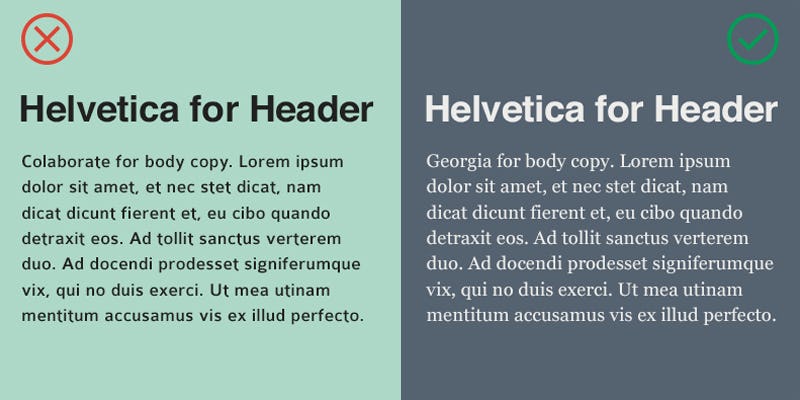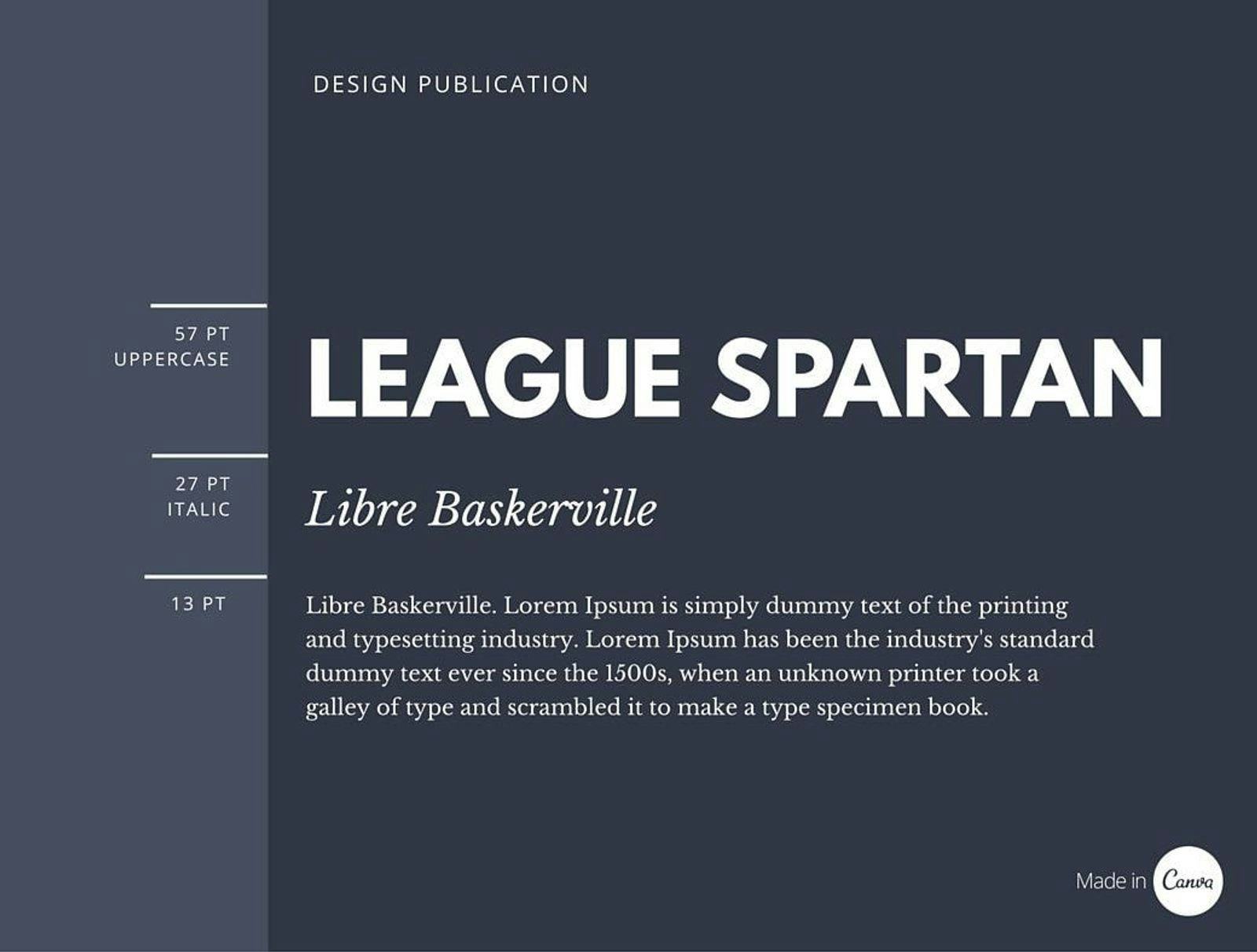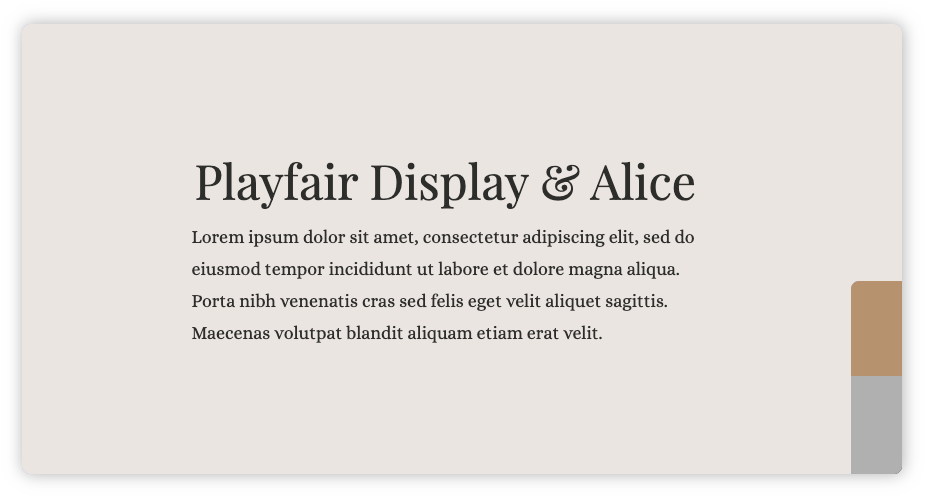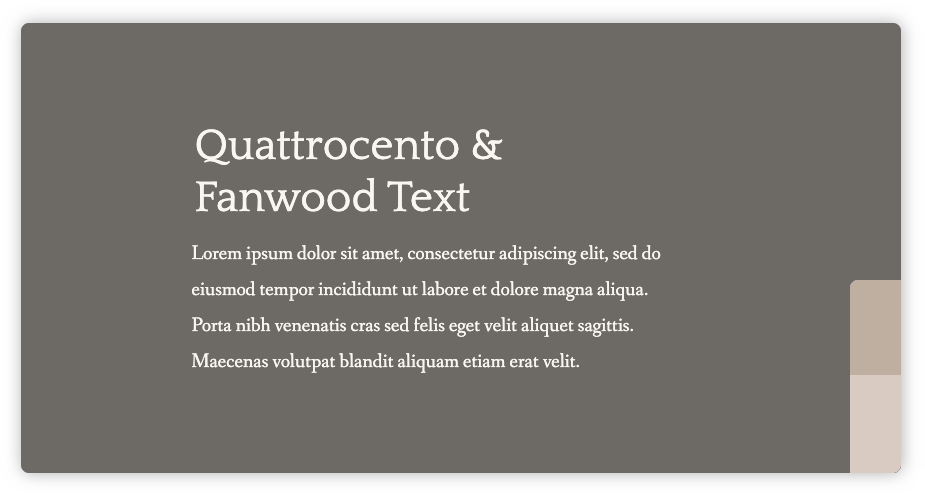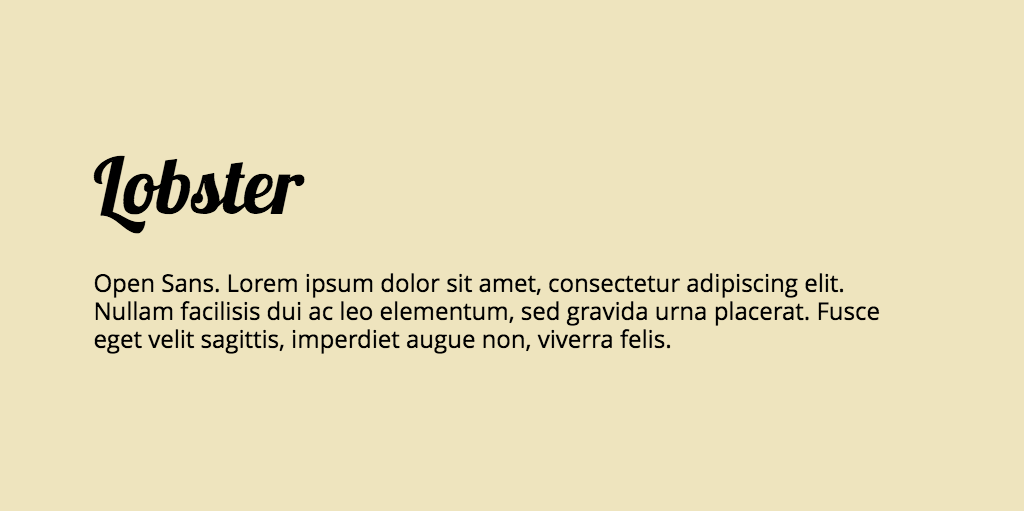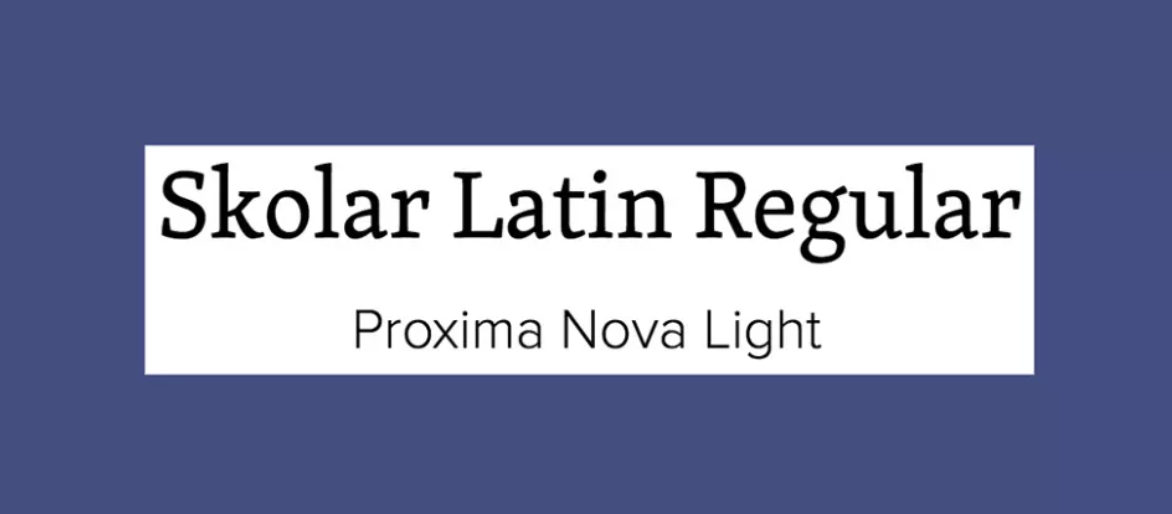
¿Te has puesto a pensar cuál es la mejor forma de combinar tipografías en un diseño? Si estás trabajando en proyectos artísticos y necesitas utilizar mucho contenido tipográfico es importante que consideres un match perfecto de fuentes que sea coherente lo que quieres comunicar.
¿Sabes cómo hacerlo? Nosotros te explicaremos en esta nota cuál es la mejor forma de combinar fuentes, qué reglas tipográficas no debes romper y cuáles son las mejores combinaciones tipográficas para hacer un match en diseño.
¿Te imaginas que tus trabajos puedan formar parte de los proyectos de diseño más populares? Aprender sobre la combinación de tipografías te puede ayudar a volver ese sueño una realidad.
1. Comprende el papel de la tipografía en el diseño
Para aprender cómo combinar tipografías, debes considerar algunas cosas, en especial, entender el papel que juegan las tipografías en el diseño gráfico. Aspectos como el contraste tipográfico y la legibilidad, entre otras cosas, hacen que un diseño bueno se diferencie de uno que no lo es.
No te preocupes si no entiendes mucho de lo que te hablamos, porque te comentaremos cada uno de los aspectos que tienen peso en el uso de las combinaciones tipográficas.
Contraste tipográfico
Si decides utilizar tipografías similares puedes crear contrastes tipográficos aplicando distintos estilos como por ejemplo: negrita, cursiva, mayúscula o minúscula.
Esta es una forma fácil de combinar las tipografías sin preocuparse de hacerlo mal, si necesitas hacer contenido de fácil lectura, utilizar fuentes similares es un excelente recurso.
Un ejemplo de contraste tipográfico es combinar una fuente negrita como Futura Medium con una letra similar; pero más delgada.
Las diferencias de estilo tipográfico hacen que el contenido en una página web o en cualquier medio digital sea más fácil de leer.
Legibilidad en la combinación de fuentes tipográficas
Una de las razones principales para combinar fuentes tipográficas serifs es la legibilidad de lectura en los libros y periódicos.
Las serifs, en la parte superior o inferior de un texto, facilitan a cualquier lector la comprensión entre caracteres de aspecto similar como la “l” mayúscula y la “l” minúscula”
Y si encuentras un sans serif con distintas formas de letras; pero legibles, no tengas miedo de experimentar y usarlas en el cuerpo del texto.
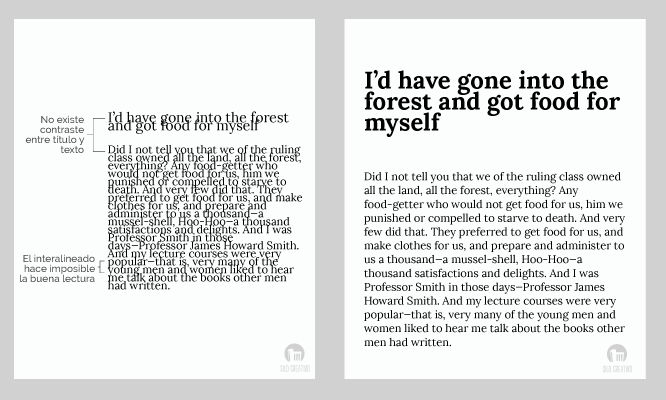
Comodidad en la combinación de letras
Muchos diseñadores web tienen el temor de utilizar una combinación de letras clásicas porque piensan que es “más de lo mismo”. Y fuentes tipográficas como Helvetica o Times New Roman muchas veces quedan en el olvido por su uso excesivo.
Sin embargo, la selección y combinación de fuentes se debería hacer pensando qué tan cómodo se siente el público al momento de leer la información de un sitio web, por ejemplo.
Por eso, no tengas vergüenza en elegir las clásicas fuentes tipográficas, sobre todo, si hacen un buen match con el diseño de un sitio web.
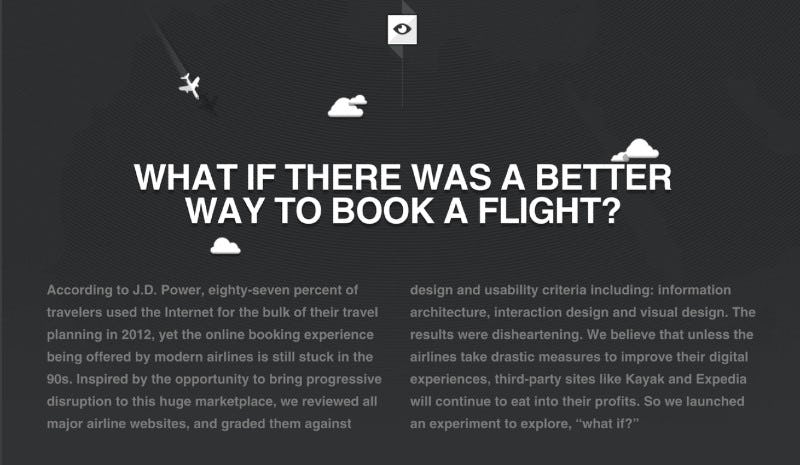
Combinación de letras para logos
Escoge tipos de fuentes con estilo que se alineen con la marca de tu cliente. La mejor forma de hacerlo es combinar letras que tengan un peso visual en el diseño de los logos.
Ten en cuenta que además de utilizar negritas, cursivas y mayúsculas; existe la posibilidad de jugar con el grosor de las letras para conseguir diferentes efectos visuales.
Pruébalos y busca el grosor perfecto para lograr el impacto visual que estás buscando. Eso sí, debes tener mucho cuidado cuando combinas las tipografías.
Combinar más de dos grosores, en un mismo diseño de logo, puede hacer que la composición quede desequilibrada visualmente.
Combinación de tipografías según la marca
Lo primero que tienes que hacer al escoger una combinación de diseño de letras para una marca es conocer la personalidad, los valores, las misión y visión de la compañía.
En pocas palabras, una marca es una lista de adjetivos o frases cortas que describen lo que quieres que los usuarios piensen de ti. ¿Y sabes cuál es la mejor forma de transmitirlo? ¡A través de la combinación de tipografías!
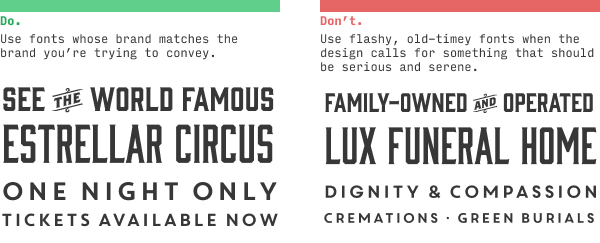
Algunos sitios web necesitan una marca que sea “limpia, simple y moderna”, mientras que otros quieren ser “modernos y lujosos”.
Y para conocer cuál es el diseño de letras que necesita tu cliente puedes tomar en cuenta estos puntos:
- Limpio y simple: letras modernas y minimalistas.
- Elegante: letras lujosas y clásicas.
- Amable: letras casuales e informales.
- Extravagante: diseño de letras innovadoras y creativas.
- Techie: letras futuristas y geeks.
2. Aprende las reglas para combinar fuentes
¿Sabías que existen reglas fundamentales para combinar fuentes?
Estos mandamientos harán que la combinación tipográfica no sea algo muy complicado, sigue estos consejos y puedes estar seguro que funcionarán con éxito en tus proyectos de diseño.
¿Listo para empezar a combinar fuentes tipográficas? Esperamos que esta información te sirva para crear mejores propuestas de diseño y además, que puedas hacer una buena combinación de tipografías en tus proyectos personales.